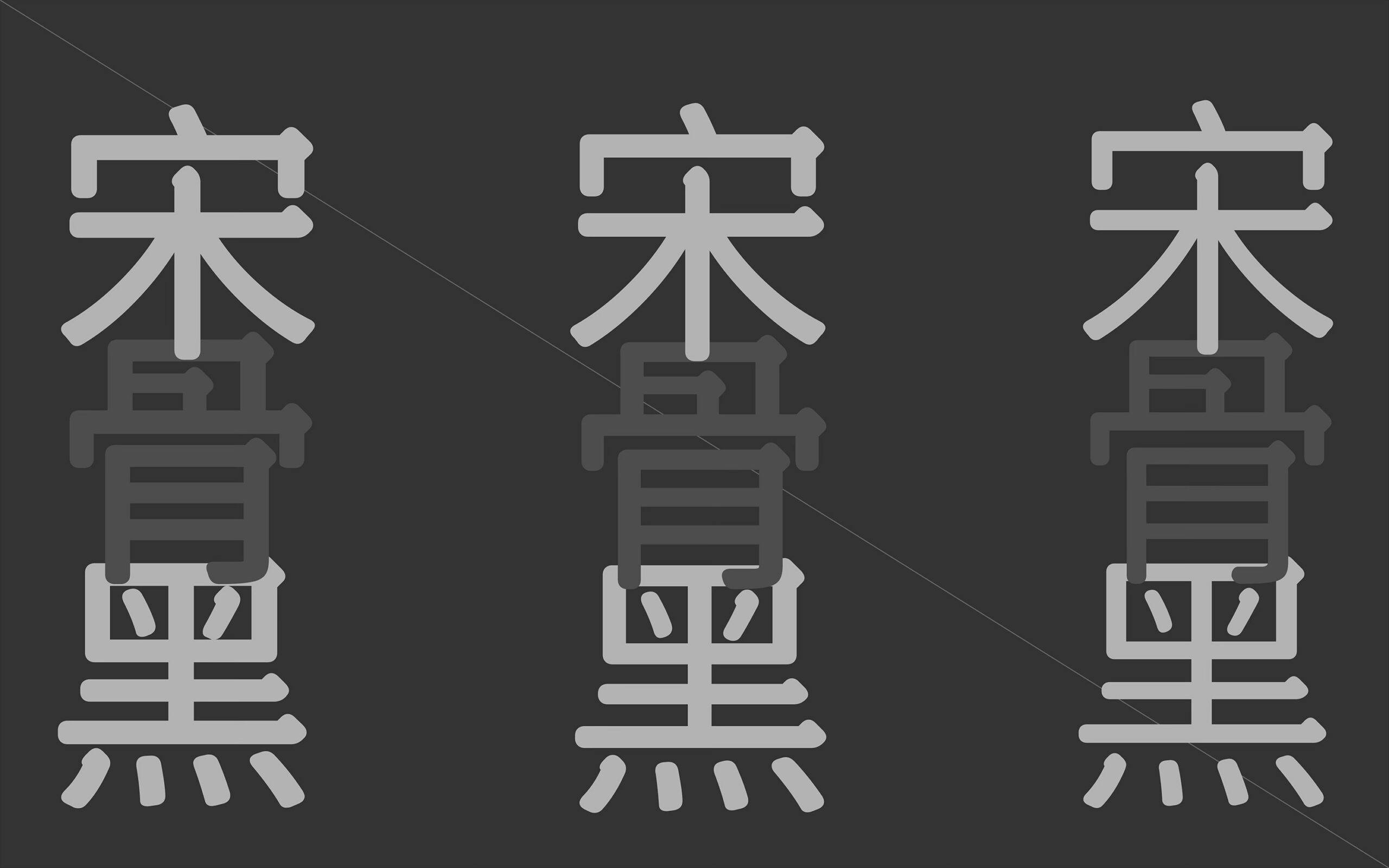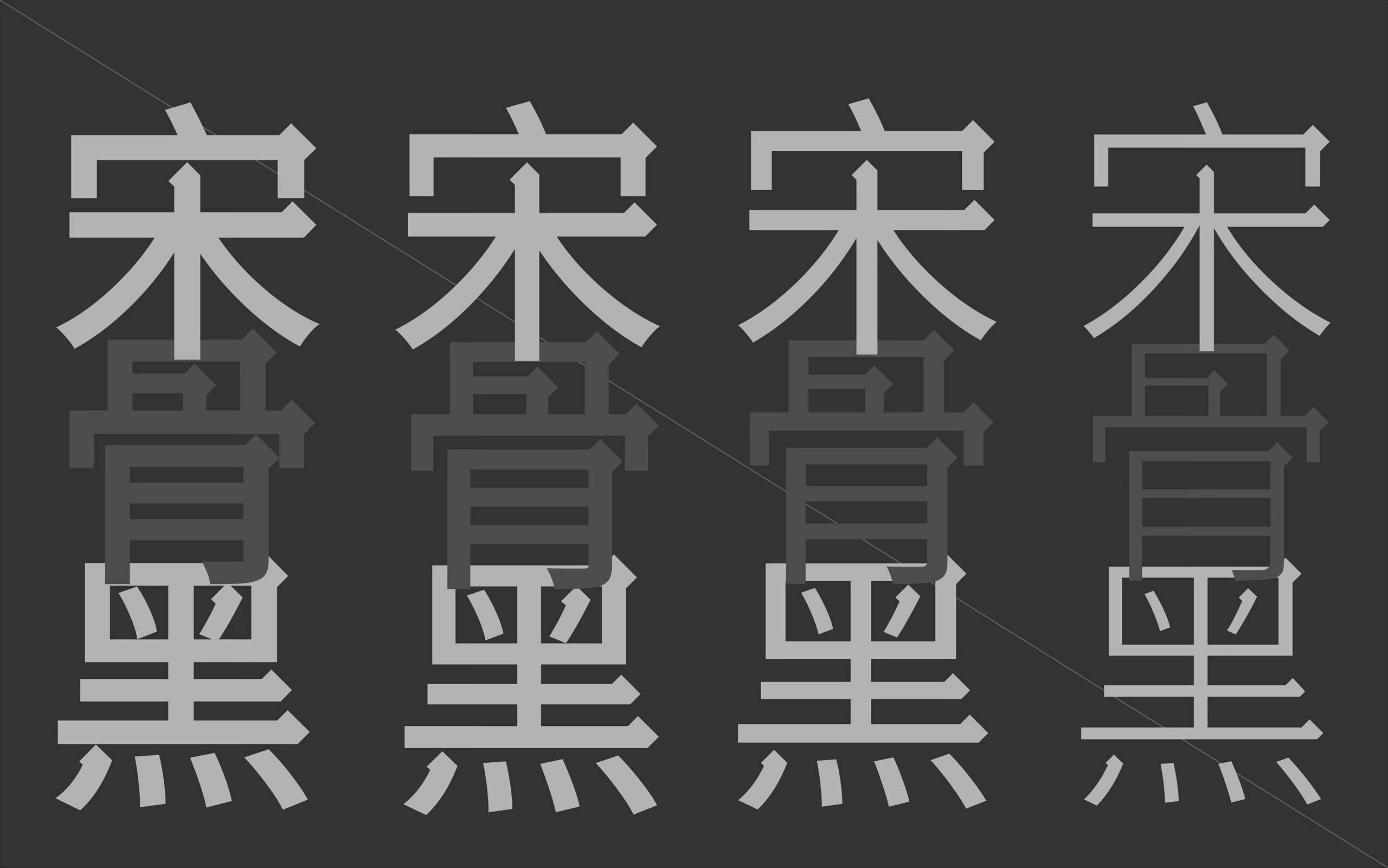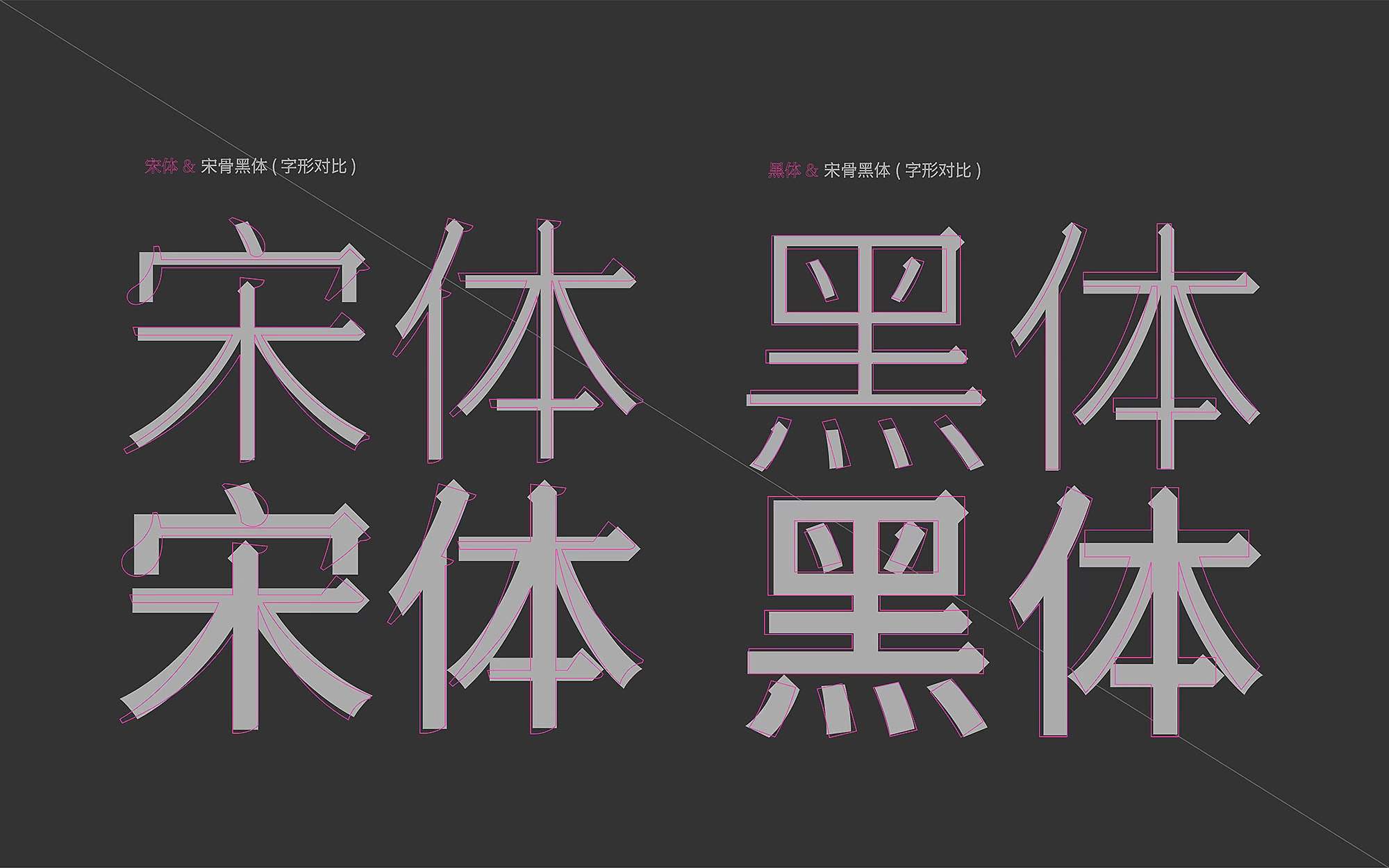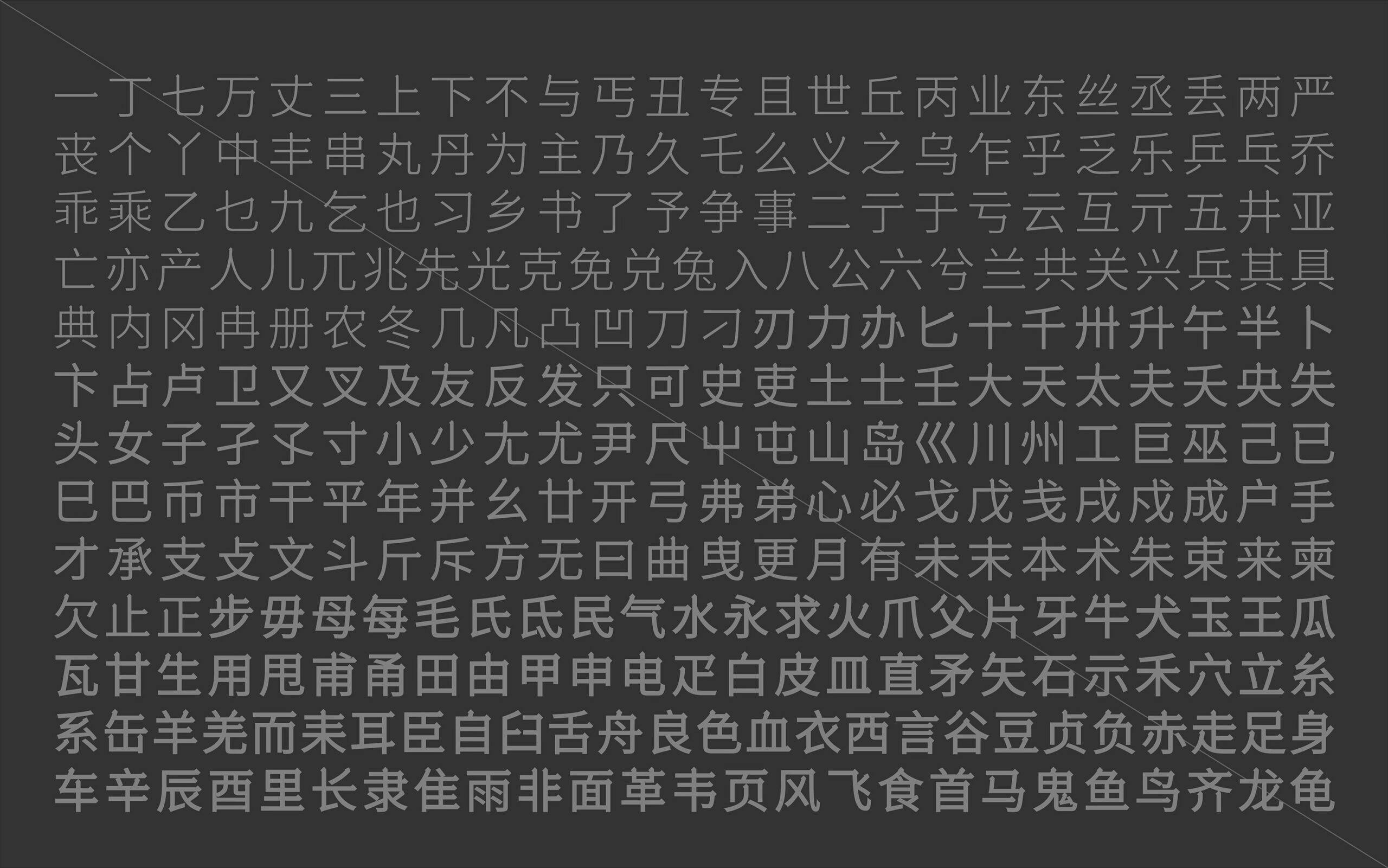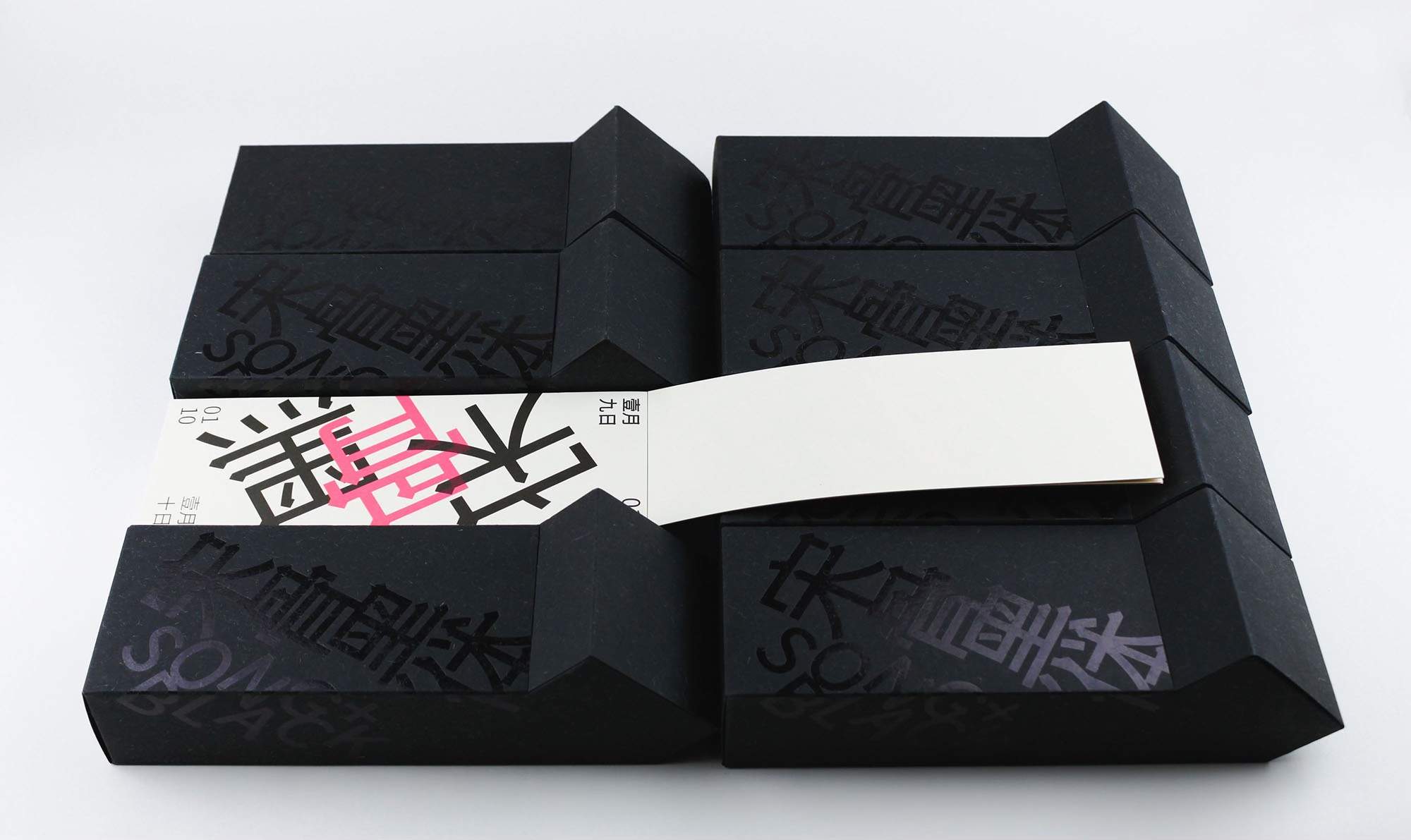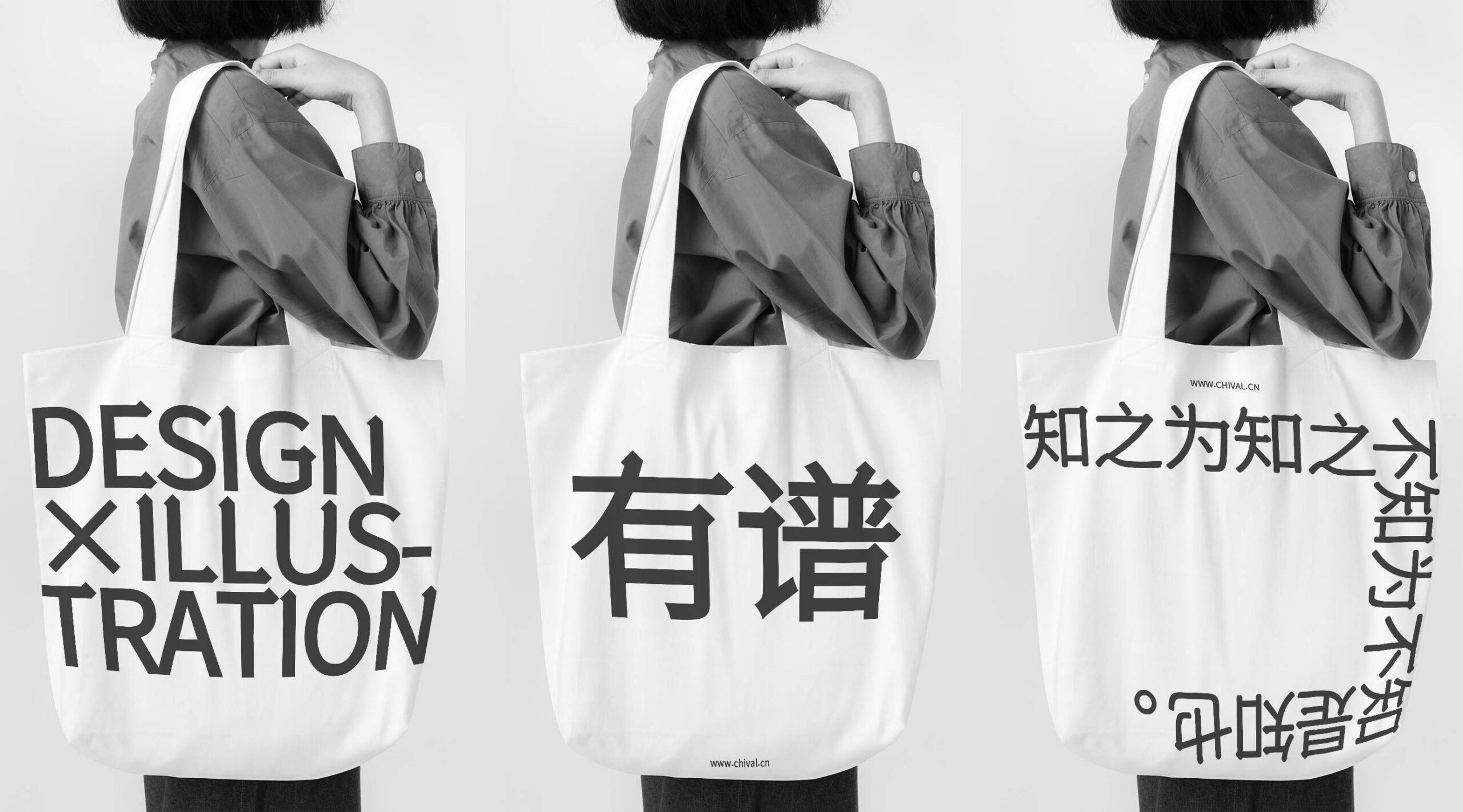
宋骨黑体是奇文雲海设计团队投入近 650 天时间精心打造的一款开源中文字体,它巧妙地将宋体和黑体的特征结合在一起。字体在设计上保留了宋体横竖笔画起收笔时的“骨节”细节,那种书写带来的顿挫感清晰可辨,同时又融入了黑体的工整骨架和现代中宫结构,使得整体字形既有宋体的传统外衣,又具备黑体的现代身型,气质独特而和谐。覆盖范围方面,字体包含了将近 7000 个汉字,涵盖了 GB2312 字符集与通用规范汉字,基本满足了中文排版的各种需求。为了适应不同设计场景,它提供了 Light、Medium 等多种字重选择,让用户可以灵活调整粗细。发布协议采用 SIL Open Font License 1.1,这意味着字体可以免费用于商业用途、修改和再分发,但修改后的版本也必须以相同协议开源,并且不能单独售卖字体文件,确保了字体的开放性和共享性。这款字体适用于多种场合,比如人文类图书的排版、品牌形象 VI 的设计、海报的标题制作、商业产品的包装以及网页界面的显示等,它既体现了书卷气,又保证了在屏幕上的良好可读性,从传统到现代的应用都能胜任。